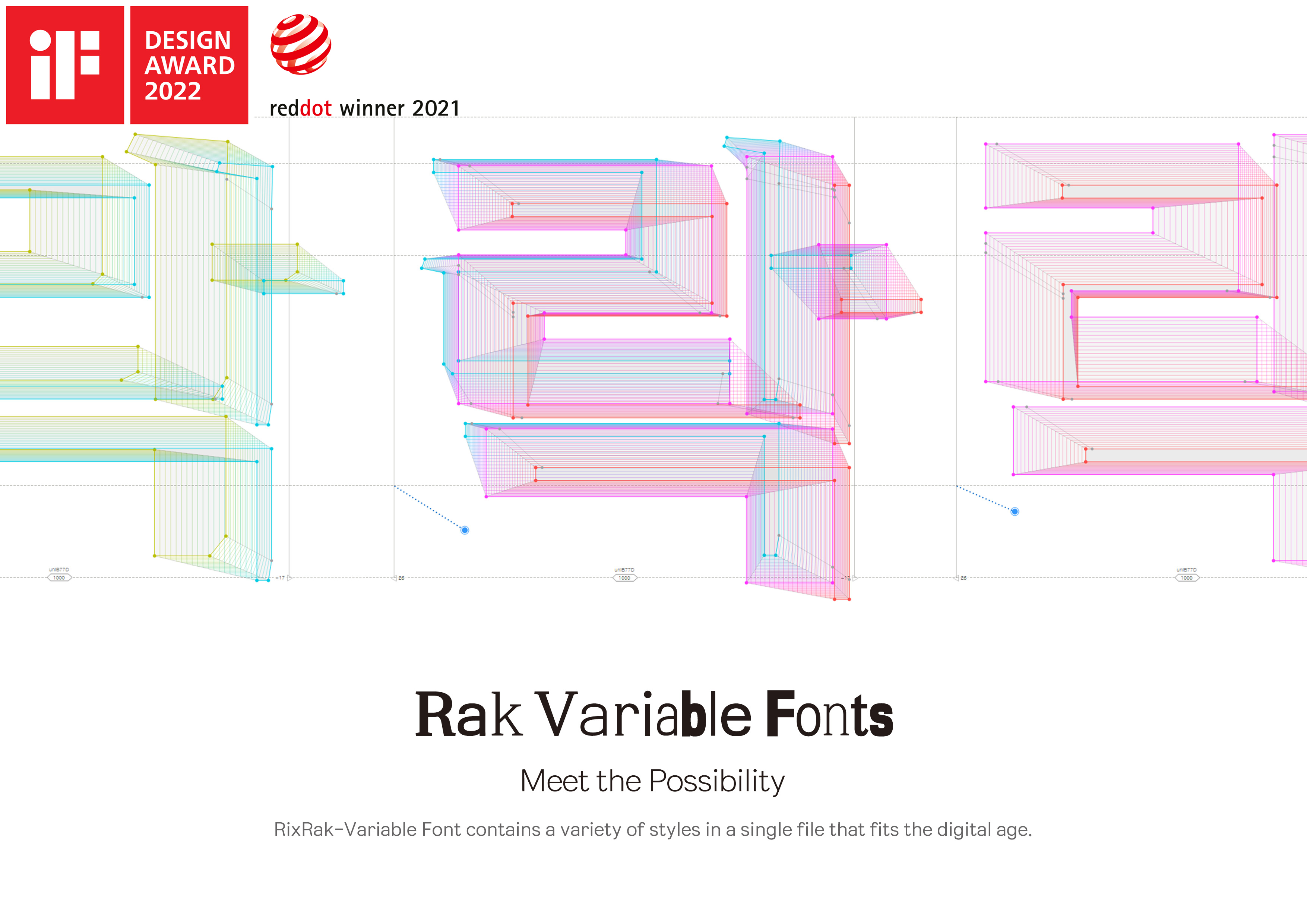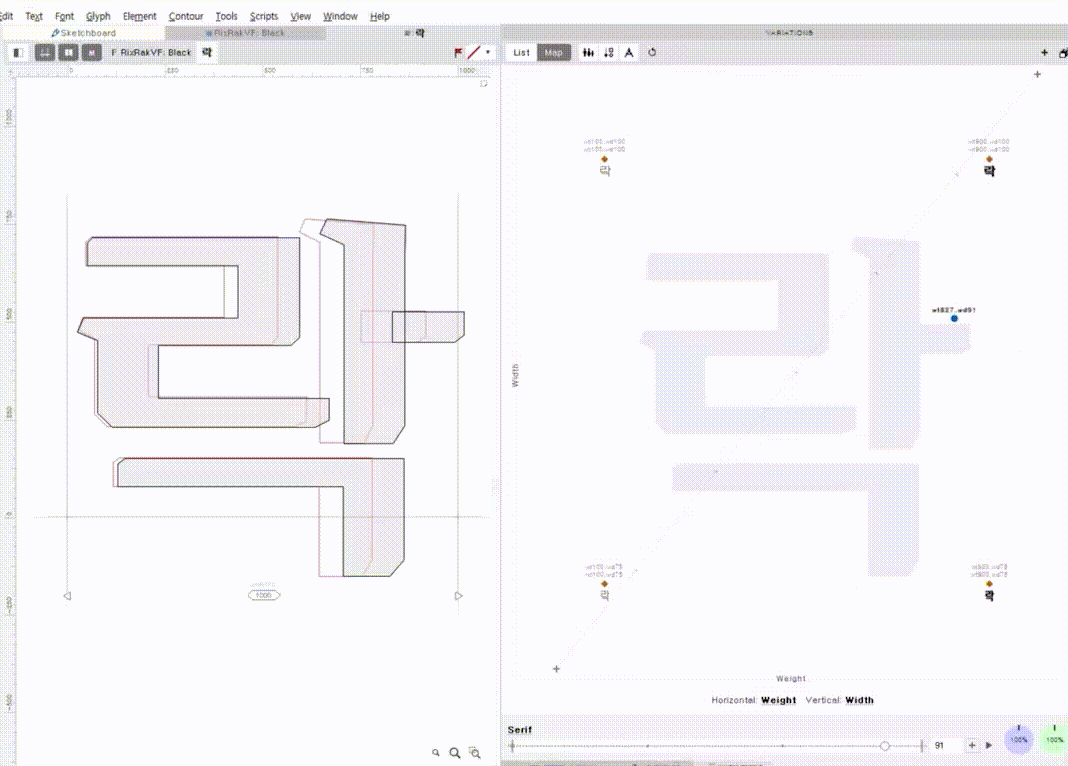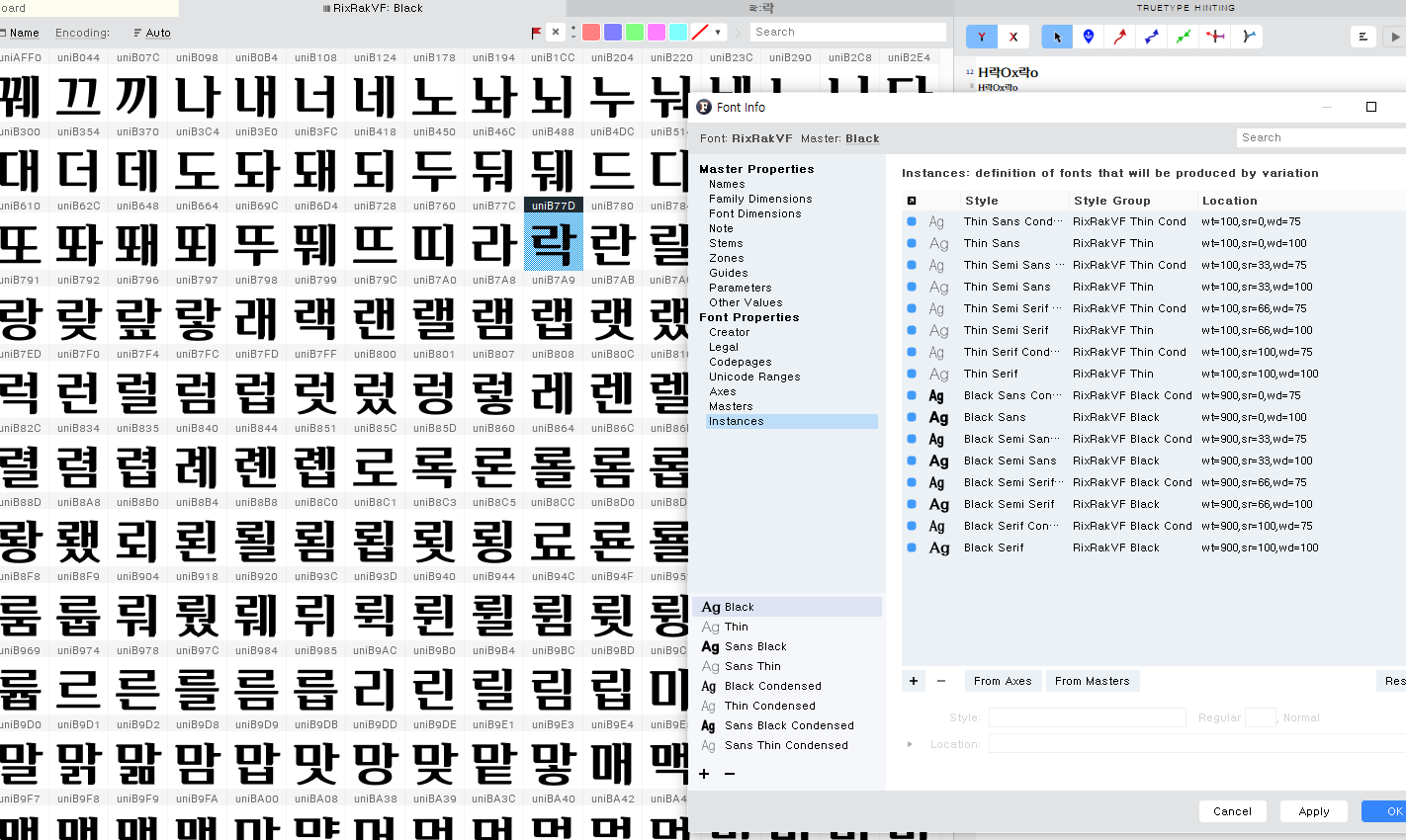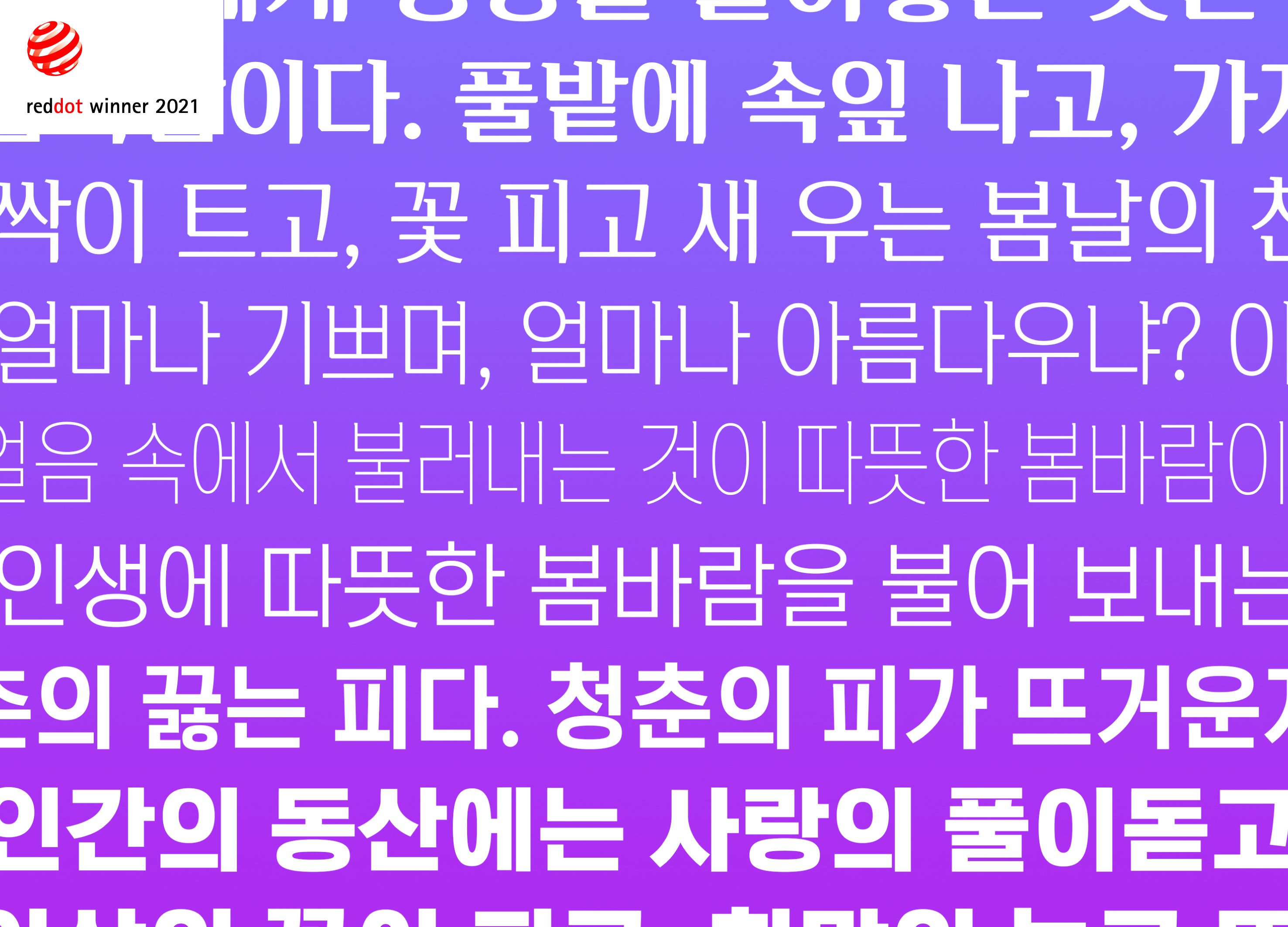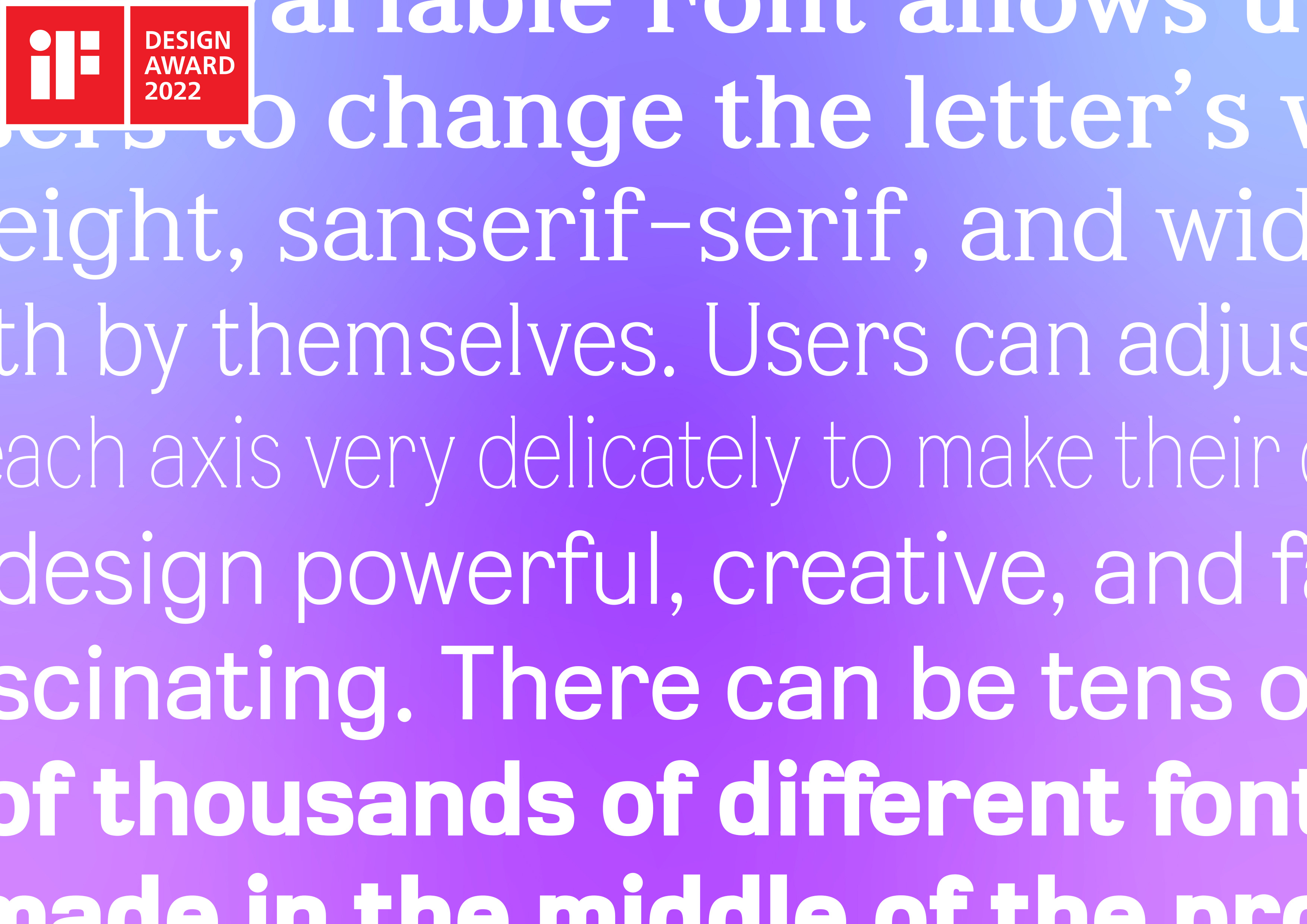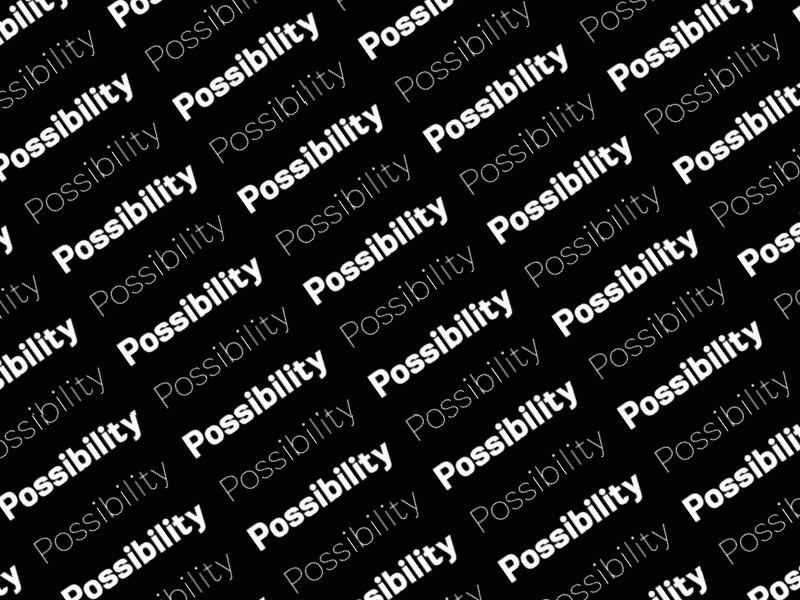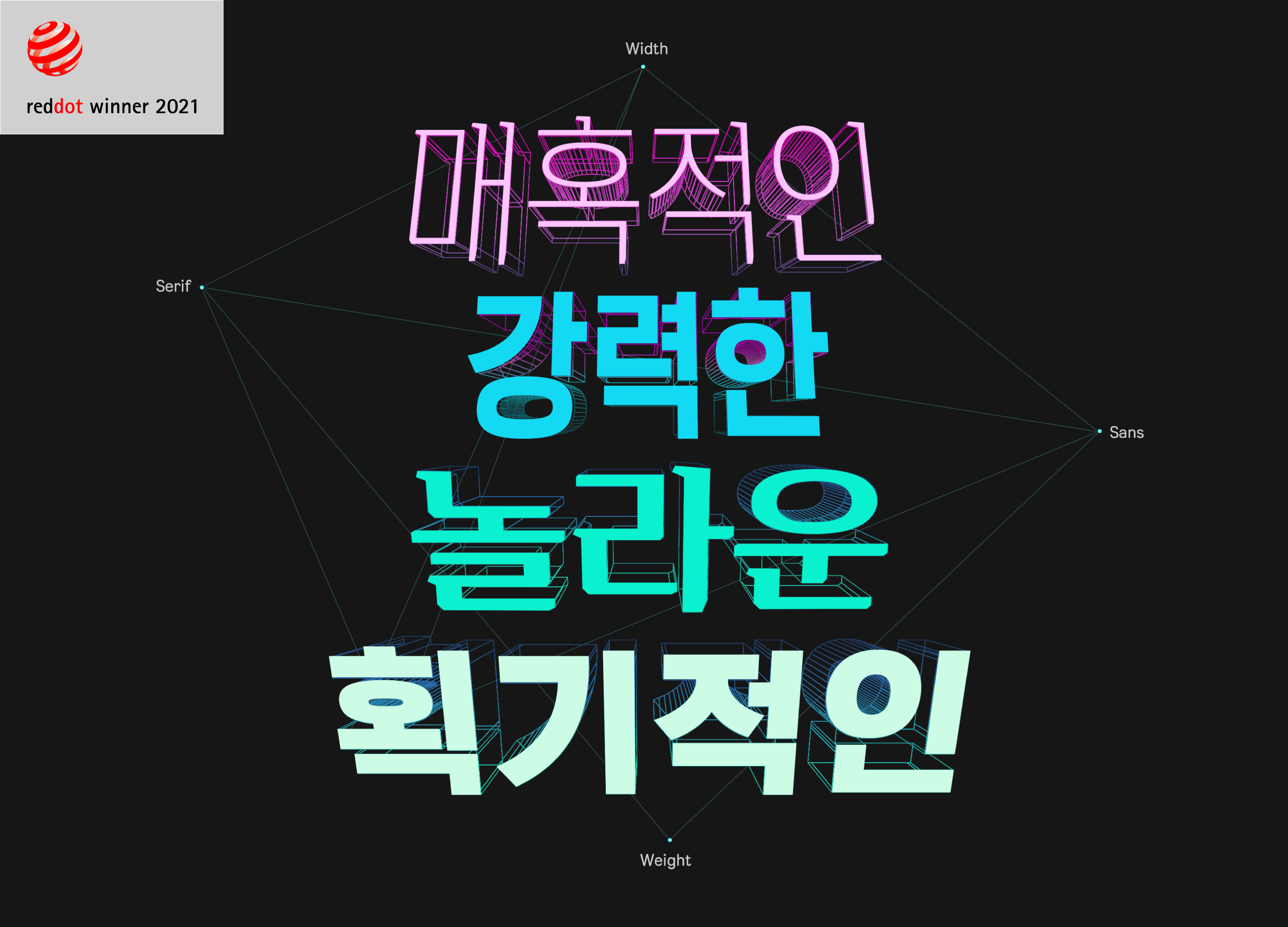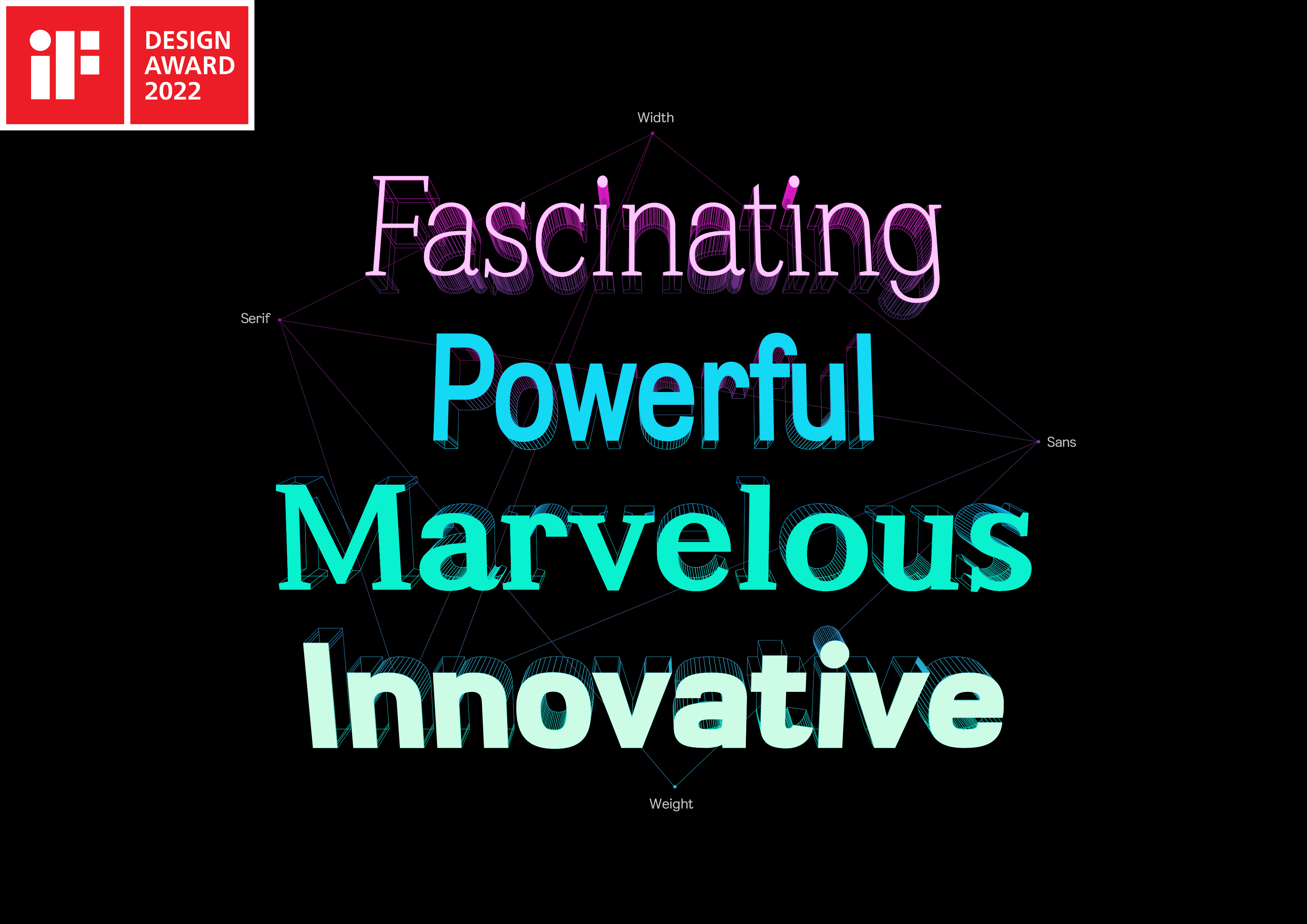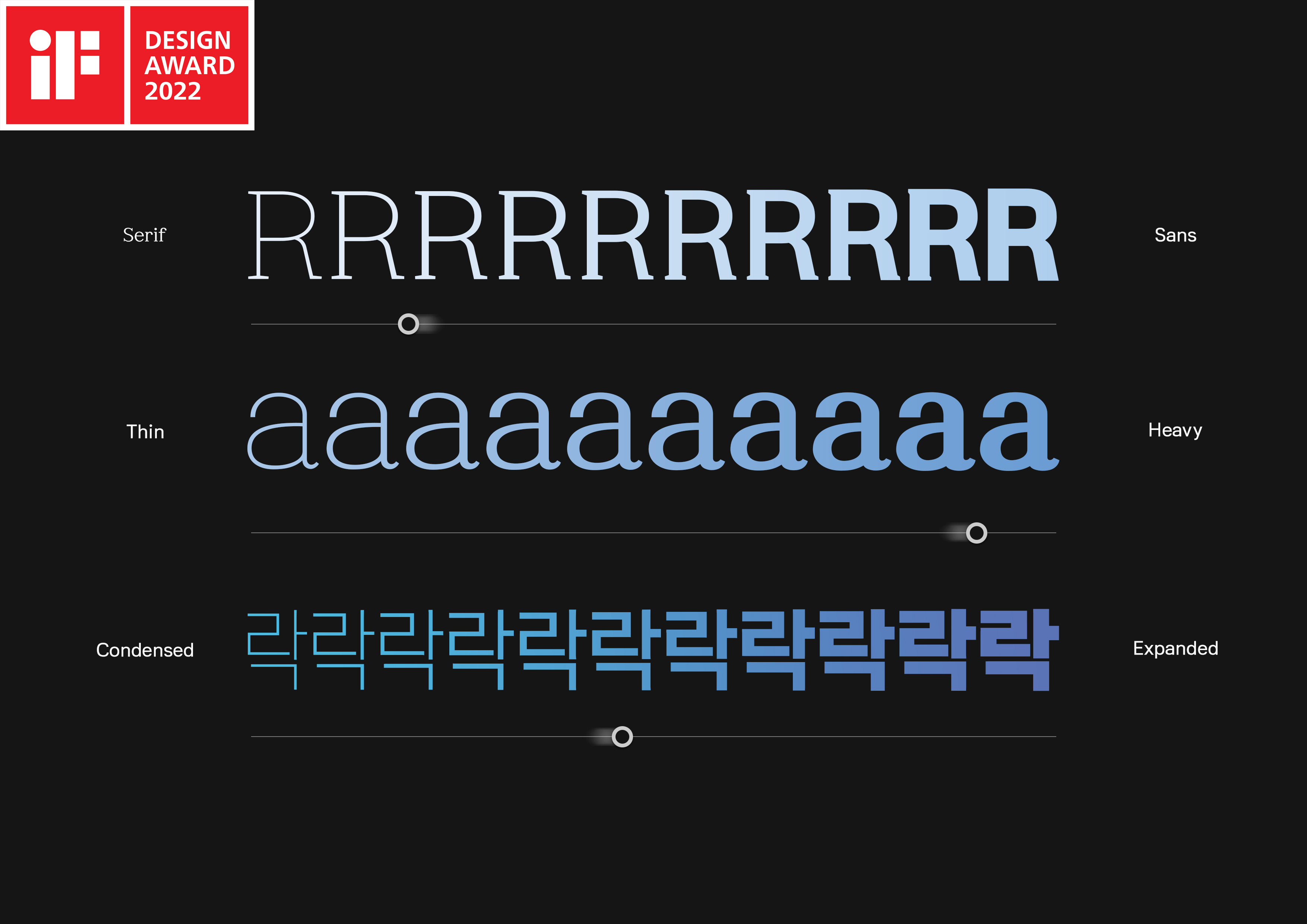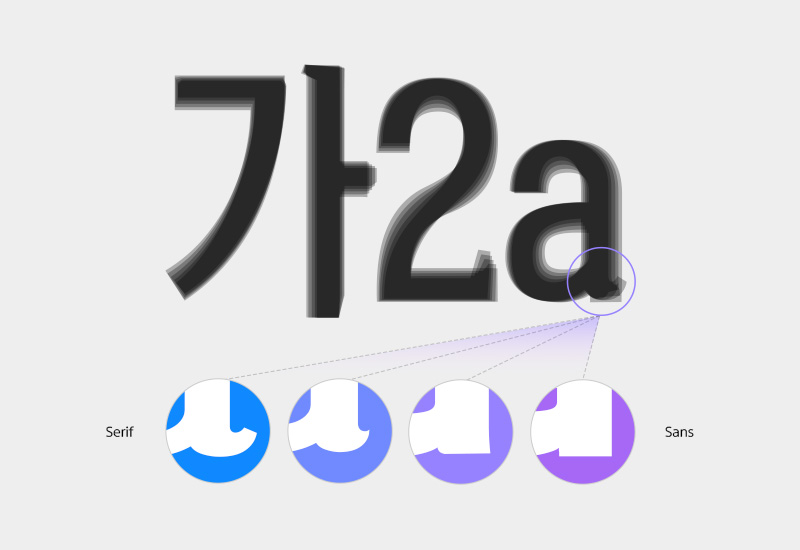
Meet the Possibility.
안녕하세요. 오늘 소개해드릴 서체는 RixFont의 첫 번째 *배리어블 폰트(Variable Font)입니다. 수개월의 노력 끝에 제작된 Rix락배리어블은 사용자가 직접 글자의 너비, 굵기, 세리프를 조정할 수 있는 특별한 한글 서체입니다. 정말 영광스럽게도 레드닷 디자인 어워드 2021 브랜드&커뮤니케이션(Red Dot Award: Brands & Communication Design 2021) 부문에서 본상인 ‘Winner’를 수상한 Rix락배리어블이 iF 디자인 어워드 2022 커뮤니케이션 부문에도 또 한번 본상을 수상했습니다.
*배리어블 폰트란?
2016년 어도비, 애플, 구글, 마이크로소프트 관계자들이 협동하여 처음 발표했던 폰트로, 하나의 폰트 파일에 여러 개의 스타일을 동시에 넣은 가변 폰트입니다. 사용자가 직접 폰트의 속성을 조정할 수 있는 축을 제공하며, 어도비 프로그램(인디자인, 포토샵, 일러스트레이터 CC 이상)에서 사용할 수 있습니다.
Rix락배리어블 폰트는 다양한 스타일을 한 파일에 담고 있으면서 경제적인 파일 크기를 가지고 있다는 점도 큰 장점인데요. 2020 K-디자인 어워드에서 Grand Prize를 수상한 Rix락-시리즈(락-산스, 락-세리프) 폰트를 업그레이드하여 제작한 것으로 위 세 가지 축으로 이루어진 상업용 배리어블 폰트는 국내 첫 시도입니다. 세계적으로 명망 높은 디자인 어워드에서 인정받은 폰트인 만큼 제작자의 애정도 남다르지 않을까 싶습니다. 이 서체를 제작한 박용락 디자이너와 이야기 나눠봤습니다.
배리어블 폰트가 참 제작하기 까다롭고 어려운 폰트라고 들었습니다. 그럼에도 왜 배리어블 폰트를 만들게 되었나요?
작년에 폰트릭스 대표 서체인 Rix락 서체 시리즈(Rix락-산스, Rix락-세리프)를 만들고 이 두 개의 서체를 보다 더 적극적으로 활용하고 홍보할 수 있는 것이 무엇일까 고민을 많이 하였습니다. 그 방법으로 최신 기술의 배리어블 폰트를 제작하는 것이 좋겠다는 생각을 하고 제작하게 되었습니다. Rix락 시리즈가 보다 풍부해지고 활용성이 올라가리라 기대해봅니다.
총 제작 소요시간은 얼마나 걸렸나요? 제작하면서 가장 어려웠던 부분은 무엇이었고 또 어떻게 극복했는지?
연구와 기획, 그리고 마무리까지 총 8개월 정도 소요되었습니다. 아무래도 최신 기술이고 한 번도 시도해 본 적이 없는 작업이라 힘이 들었습니다. 기존에는 폰트랩 5를 주로 사용하였는데, 배리어블 폰트는 폰트랩 7에서 작업이 가능하기 때문에 프로그램을 다시 익혀야만 했습니다. 폰트랩 5와 폰트랩 7은 이름만 같을 뿐 새로운 프로그램에 가까울 정도로 많이 다릅니다.
많은 시행착오를 거쳐 겨우 기능 하나하나를 알아가기를 반복하며 작업해 나가야 했습니다. 또한 겉으로 보기에는 한 개의 폰트지만 그 안에 탑재되어 있는 폰트는 총 8개의 다른 서체가 들어가 있습니다. 즉 8개의 서체가 합쳐져서 하나의 폰트가 된 것이지요. 합칠 때도 폰트의 속성을 일일이 다 맞춰야만 합니다. 그 속성이란 점의 순서와 개수, Element의 순서와 개수를 8개 서체 모두 맞춰야만 하는 힘든 작업이었습니다. 그만큼 작업의 시간도 더딜 수밖에 없었습니다. 이러한 어려운 과정이 있을 거라 알았더라면 배리어블 폰트를 시도하지 않았을 수도 있겠네요.(웃음) 새로운 시도를 하고 이를 꼭 해내야 한다는 마음과 이상민 디자이너와 함께 했기 때문에 가능했습니다.
정말 이야기만 들어도 굉장한 시간과 노력이 들어갔다는 생각이 드네요. 일반 사람들에겐 생소할 수 있는 배리어블 폰트, 어떻게 사용하면 가장 효율적일까요?
배리어블 폰트가 어도비 일부 제품에서만 사용 가능하기 때문에 어도비 제품을 쓰시지 않는 분들은 배리어블 폰트 사용이 어렵습니다. 다만 배리어블 폰트라고 하더라도 그 중간값에 해당하는 폰트로는 설정이 가능하니 중간값이 필요한 분들은 그 서체로 일반 프로그램에서 선택하셔서 사용하시면 됩니다.
앞으로 또 다른 배리어블 폰트를 제작한다면 어떤 스타일을 제작해보고 싶으세요?
배리어블 폰트를 또 제작할 수 있을지...^^ 앞서 말한 대로 너무 힘든 작업이라서요. 만약 제작하게 된다면 고딕과 세리프의 변화가 아닌 골격이 변하는 배리어블 폰트를 만들어 보고 싶습니다.
폰트의 가능성을 만나다.
Rix락배리어블 폰트(이하 락VF)는 디지털 시대에 적합한 다양한 스타일을 한 폰트에 담고 있는 서체 입니다. 하나의 폰트로 다양한 스타일을 구현할 수 있을 뿐만 아니라 경제적인 파일 크기를 가지고 있어 디자인 작업 시 매우 유용하고 효율적입니다. 어떤 매력들이 있는지 한 번 하나씩 알아볼게요.
다채로운 style을 담다
락VF는 다채로운 스타일을 가지고 있는 폰트입니다. 세리프, 산세리프(고딕), 얇게, 굵게, 좁게, 넓게 모든 것을 내가 원하는 정도로 조절할 수 있는 신개념의 서체죠.
축의 이동을 통해 수 천, 수 만 가지의 다른 폰트가 탄생할 수 있습니다. 세리프-산세리프, 글자 굵기, 글자 너비 이렇게 세 가지 축으로 된 배리어블 폰트는 국내에서 첫 시도인데요. 그만큼 메리트가 있고 높은 기술력이 들어간 폰트입니다.
제목용! 본문용? 다 되는 폰트
축을 조정해 세리프의 정도를 매우 세밀하게 조절할 수 있으며, 용도에 맞게 효율적으로 활용하기 좋습니다. 두께를 굵게 Sans로 설정해 레트로 느낌의 타이틀로 활용할 수도 있고, Serif를 주어 두께를 얇게 조정해 본문에 사용할 수도 있습니다. 덕분에 통일감 있으면서도 단조롭지 않은 디자인이 가능해요!
Variable YOURSELF
락VF는 어도비 프로그램을 통해 쉽게 활성화하여 사용할 수 있는데요. 사용자가 직접 각각의 축으로 폰트의 두께, 세리프, 폭을 조정할 수 있습니다. 하나의 폰트로 다른 특징을 가진 여러 서체를 만들어낼 수 있습니다.
| Rix락배리어블 적용 이미지 샘플
락VF는 한글 2,350자, 라틴 95자, 약물도 58자를 지원합니다. 영문과 여러 기호들도 배리어블하여 디자인 작업에 효율적으로 활용해 보세요. 인쇄물은 물론 웹, UI, 영상 자막 등 다양한 방면의 디지털 환경에서 활용도가 높은 폰트입니다.